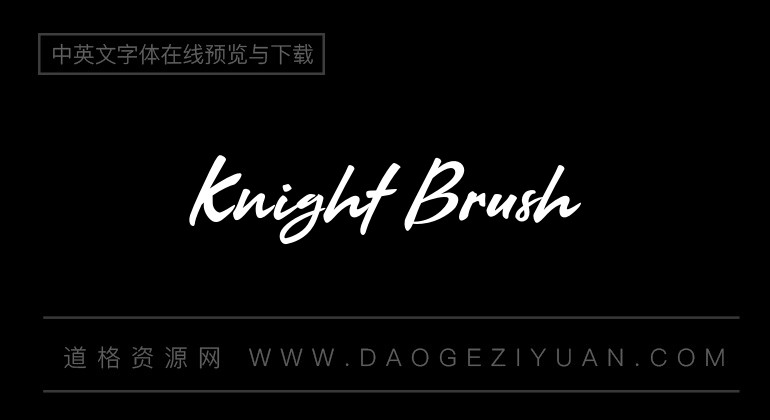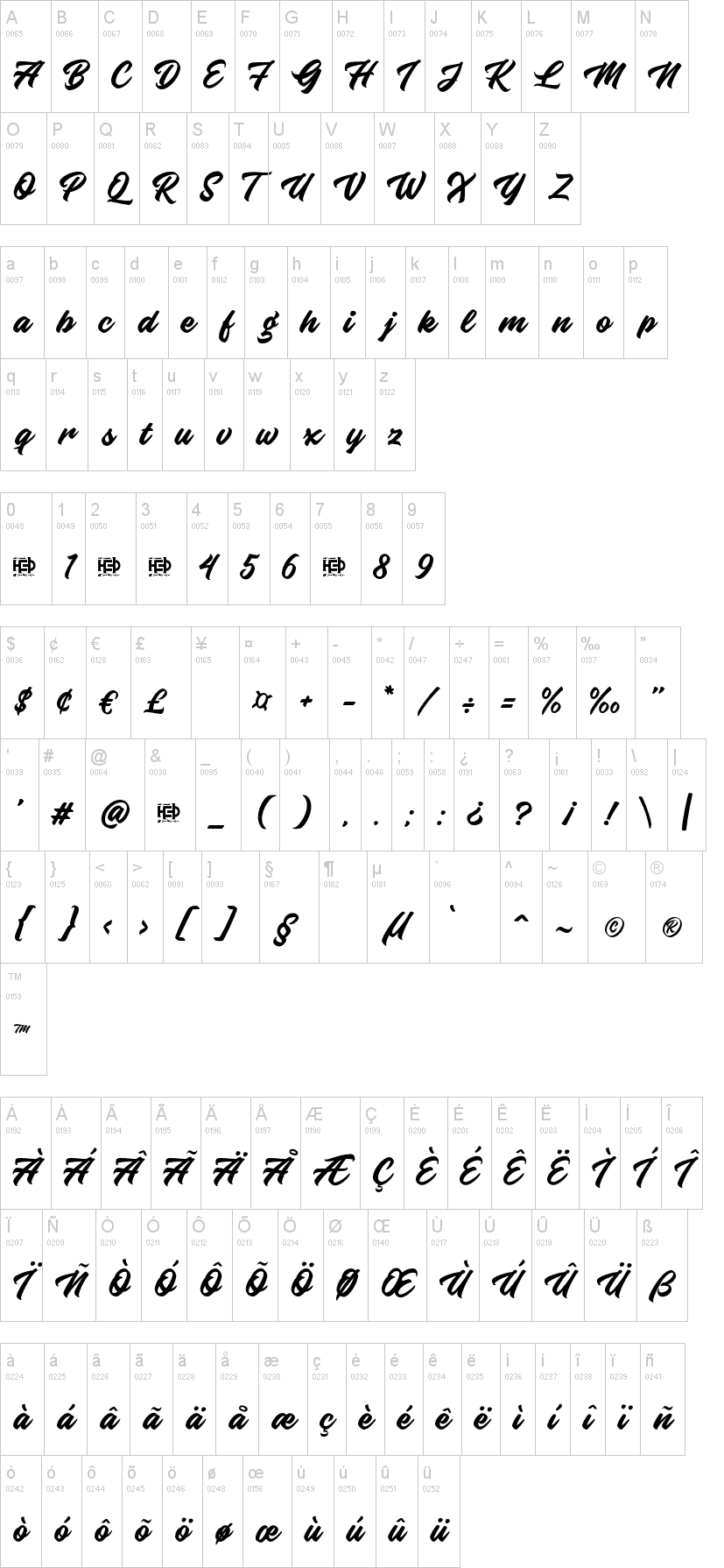
Knight Brush 是一种手写风格的字体,具有生动、自然、粗犷的特点。它的笔画有明显的笔触,仿佛是用毛笔书写而成的,因此具有一定的艺术感和个性化特点。 Knight Brush 字体适用于设计广告、海报、标志、包装等领域,可以帮助设计师打造出具有独特魅力的作品。内容介绍
Knight Brush是一款非常不错的手写艺术字体,具有很好的视觉感,适合于文化类的宣传设计、商业类品牌的广告和产品包装设计以及个性化文字排版等较多场景。